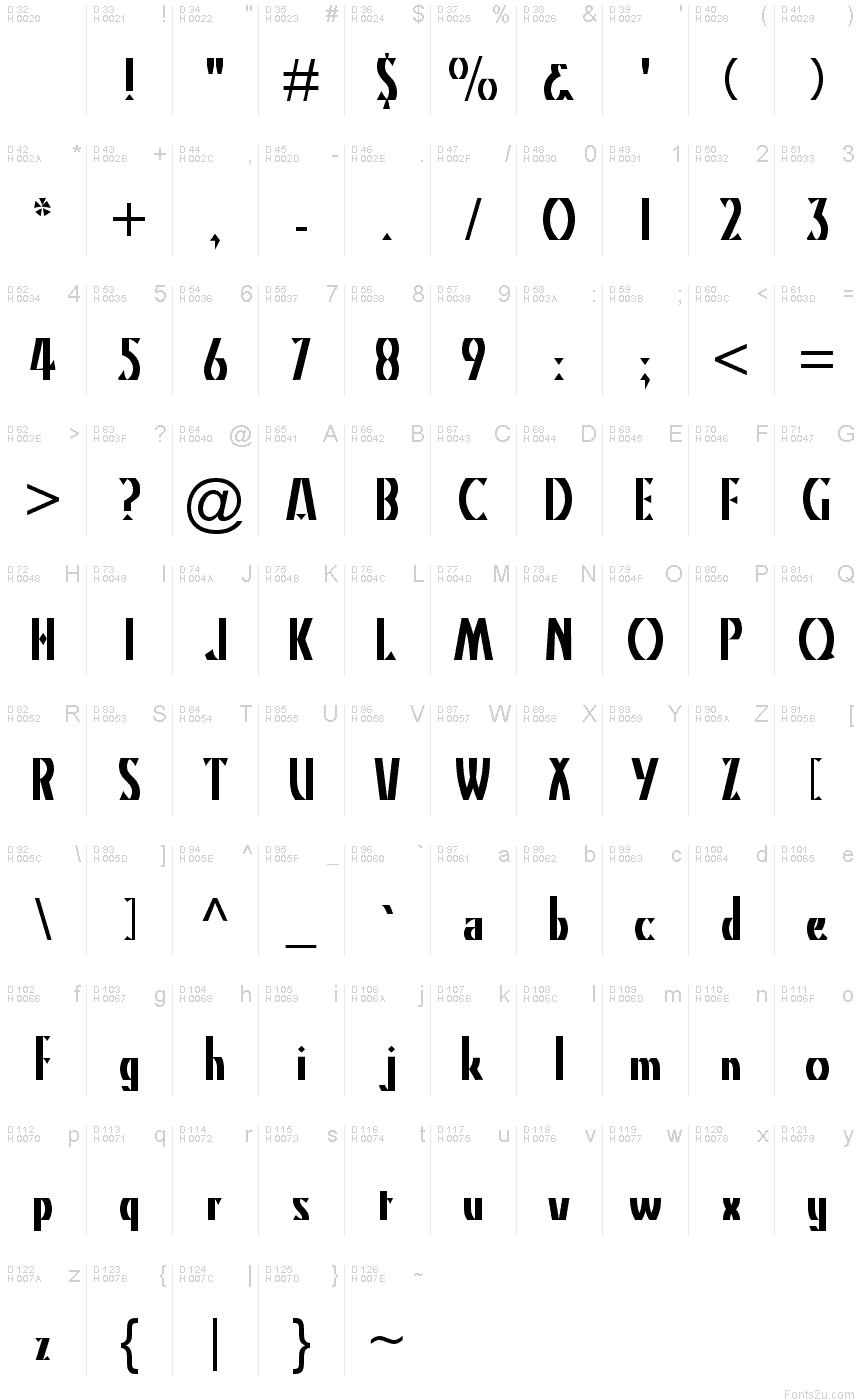
VPS Ha Tien
VPS Ha Tien od VPS Font je bezplatné, vysoce kontrastní titulkové písmo s výrazným vietnamským redakčním nádechem. Písmena jsou vysoká a elegantní, tvořená ostrými svislými tahy, výraznými patkami typu slab a několika diamantovými akcenty. To vše dodává sadě ceremoniální eleganci připomínající ručně malované nápisy, nikoliv neutrální knižní styl.
Toto bezplatné písmo se skvěle hodí pro branding restaurací, kulturní plakáty, obálky knih, titulní karty a obaly, kde záleží na rafinovaném místním charakteru. Dobře funguje i v krátkých nadpisech a iniciálách připomínajících monogramy, protože úzké, vysoké tvary a ozdobné detaily vytvářejí silný dojem i bez velkého množství znaků.